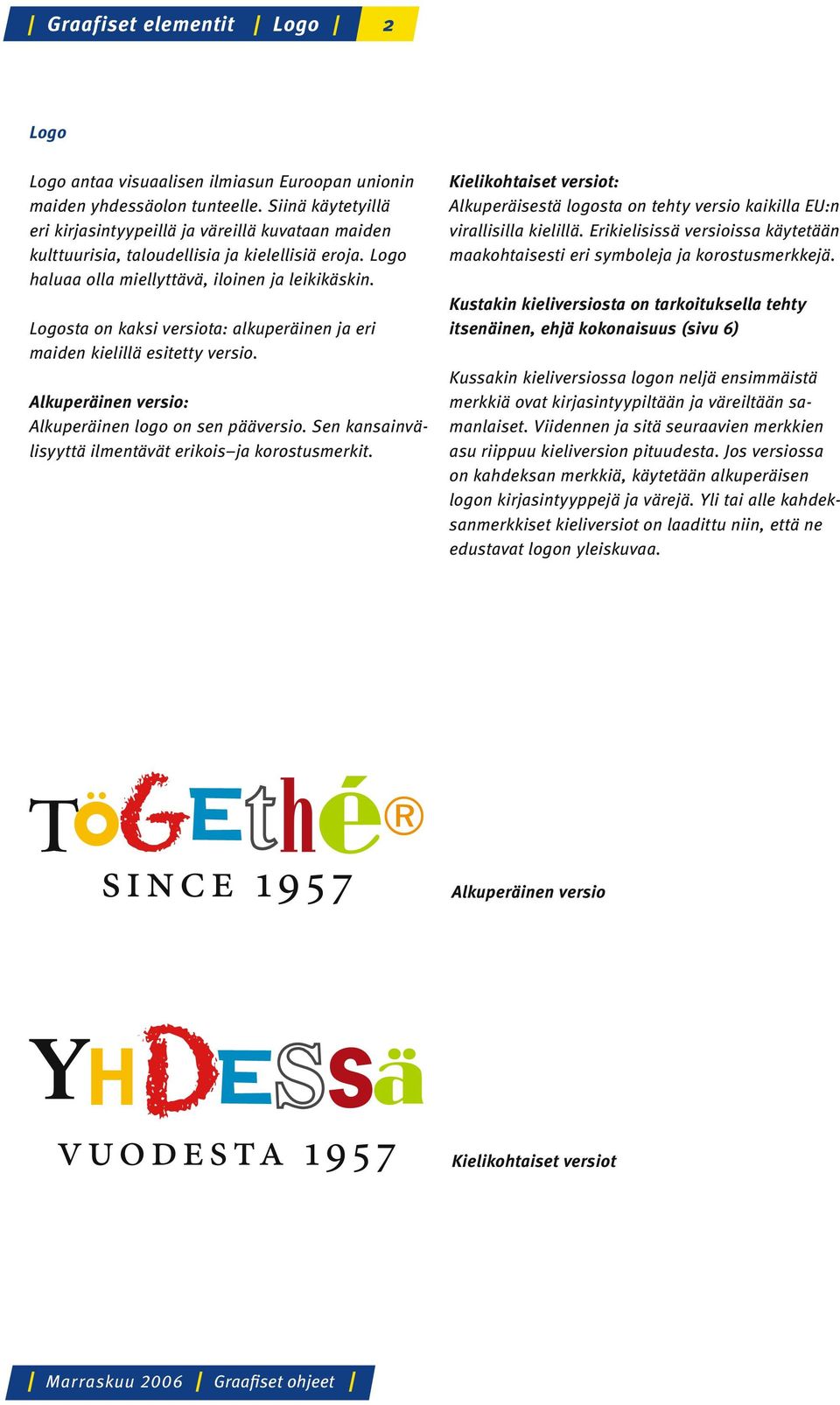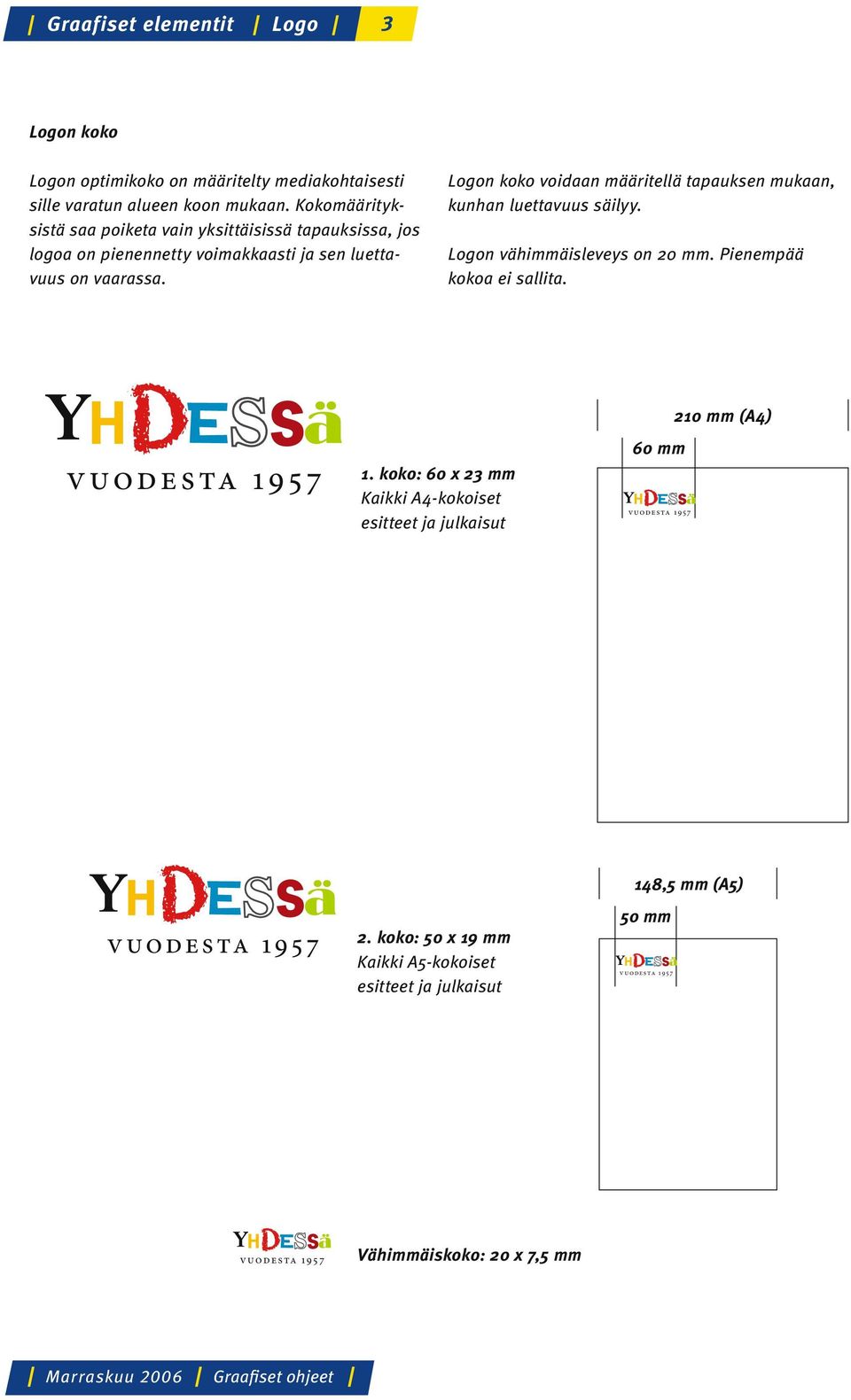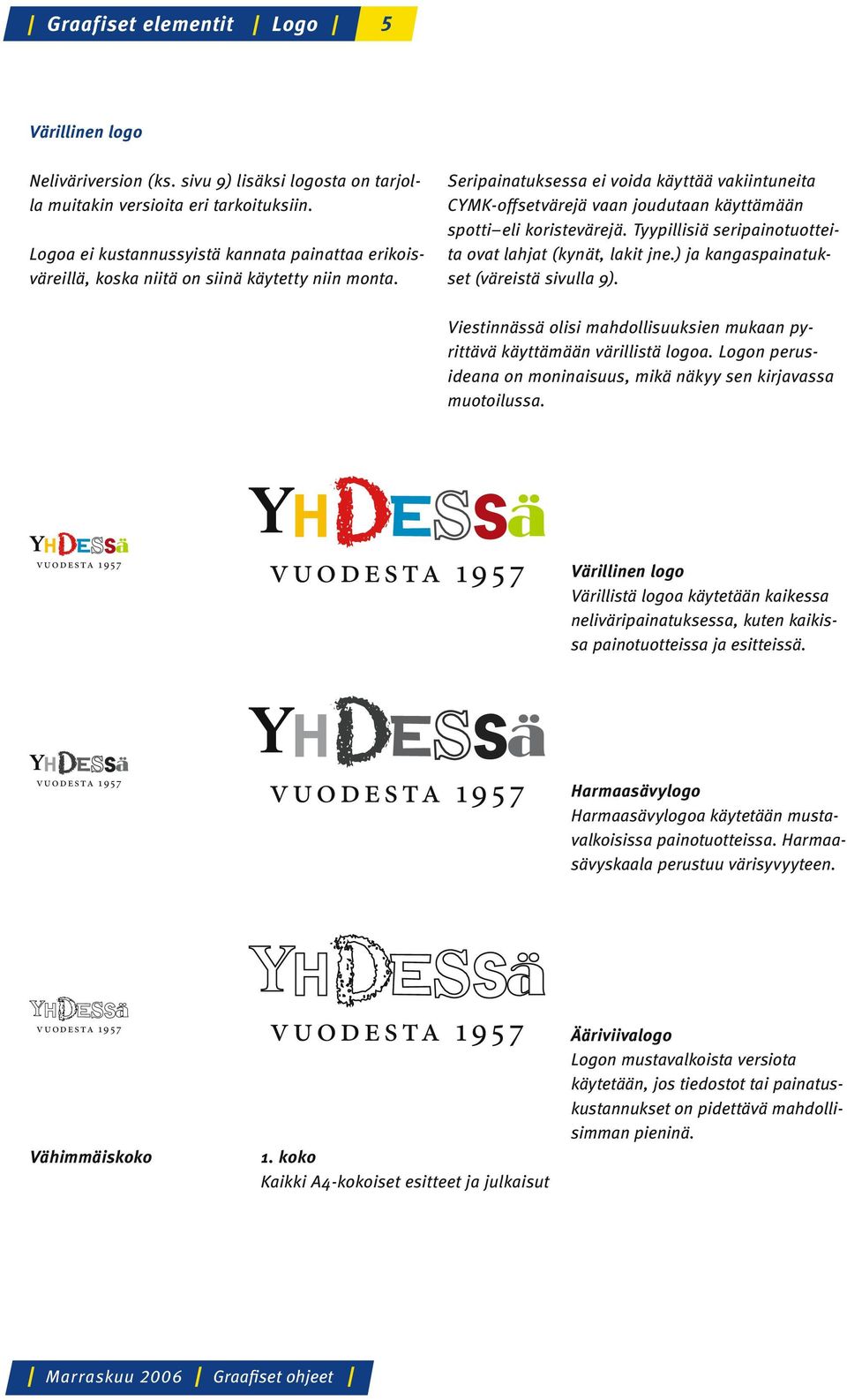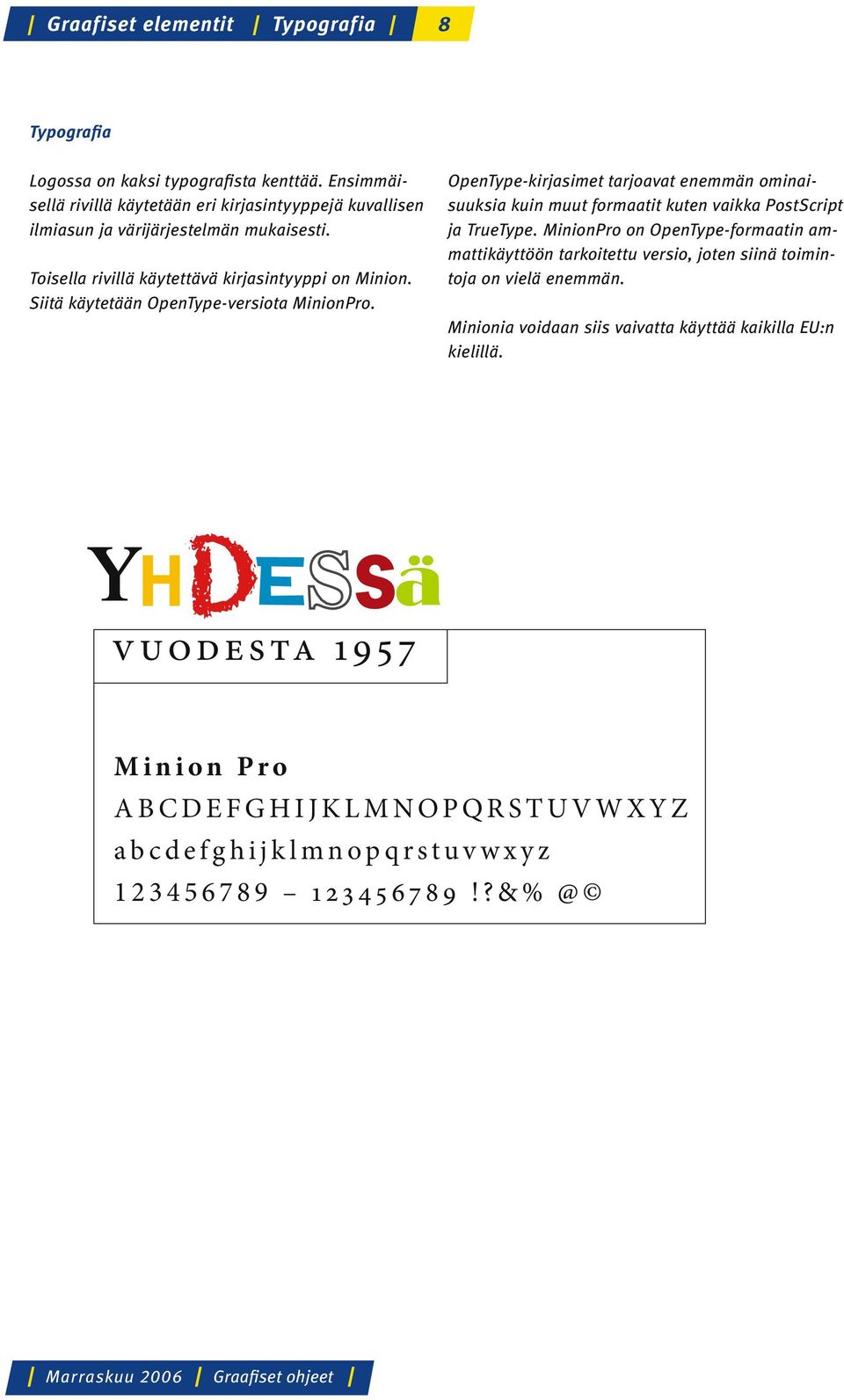
2 Graafiset elementit Logo 2 Logo Logo antaa visuaalisen ilmiasun Euroopan unionin maiden yhdessäolon tunteelle. Siinä käytetyillä eri kirjasintyypeillä ja väreillä kuvataan maiden kulttuurisia, taloudellisia ja kielellisiä eroja. Logo haluaa olla miellyttävä, iloinen ja leikikäskin. Logosta on kaksi versiota: alkuperäinen ja eri maiden kielillä esitetty versio. Alkuperäinen versio: Alkuperäinen logo on sen pääversio. Sen kansainvälisyyttä ilmentävät erikois ja korostusmerkit. Kielikohtaiset versiot: Alkuperäisestä logosta on tehty versio kaikilla EU:n virallisilla kielillä. Erikielisissä versioissa käytetään maakohtaisesti eri symboleja ja korostusmerkkejä. Kustakin kieliversiosta on tarkoituksella tehty itsenäinen, ehjä kokonaisuus (sivu 6) Kussakin kieliversiossa logon neljä ensimmäistä merkkiä ovat kirjasintyypiltään ja väreiltään samanlaiset. Viidennen ja sitä seuraavien merkkien asu riippuu kieliversion pituudesta. Jos versiossa on kahdeksan merkkiä, käytetään alkuperäisen logon kirjasintyyppejä ja värejä. Yli tai alle kahdeksanmerkkiset kieliversiot on laadittu niin, että ne edustavat logon yleiskuvaa. since 1957 Alkuperäinen versio Kielikohtaiset versiot
3 Graafiset elementit Logo 3 Logon koko Logon optimikoko on määritelty mediakohtaisesti sille varatun alueen koon mukaan. Kokomäärityksistä saa poiketa vain yksittäisissä tapauksissa, jos logoa on pienennetty voimakkaasti ja sen luettavuus on vaarassa. Logon koko voidaan määritellä tapauksen mukaan, kunhan luettavuus säilyy. Logon vähimmäisleveys on 20 mm. Pienempää kokoa ei sallita. 1. koko: 60 x 23 mm Kaikki A4-kokoiset esitteet ja julkaisut 60 mm 210 mm (A4) 2. koko: 50 x 19 mm Kaikki A5-kokoiset esitteet ja julkaisut 148,5 mm (A5) 50 mm Vähimmäiskoko: 20 x 7,5 mm
4 Graafiset elementit Logo 4 Suoja-alue on logon ympärillä oleva tila, jonka ansiosta logo erottuu läheisyydessä olevista graafisista elementeistä. Suoja-alueen koon perustana oleva yksikkö saadaan ensimmäisestä kirjaimesta, ja sen mittasuhteet määritellään suhteessa ensimmäisen kirjaimen kokoon. Suoja-aluetta on pidettävä vähimmäisvaatimuksena. Logon tausta voi olla yksivärinen joko valkoinen tai jokin vaalea väri. Logon ja EU:n lipun asemointi Jotta logon ja Euroopan unionin välille muodostuisi suora yhteys, logoa olisi käytettävä yhdessä EU:n lipun kanssa. Logon ja EU:n lipun väliin jätetään suoja-alue (optimi ja minimietäisyys), kuten alla havainnollistetaan. Logo on asetettava valkoiselle taustalle, jotta se on varmasti luettava. Siksi sekä logo että EU:n lippu olisi painotuotteissa hyvä sijoittaa valkoiselle palkille. Näin brändi olisi helposti tunnistettavissa. < = optimum distance between two logo 210 mm (A4) 60 mm < < < minimum distance between two logo
5 Graafiset elementit Logo 5 Värillinen logo Neliväriversion (ks. sivu 9) lisäksi logosta on tarjolla muitakin versioita eri tarkoituksiin. Logoa ei kustannussyistä kannata painattaa erikoisväreillä, koska niitä on siinä käytetty niin monta. Seripainatuksessa ei voida käyttää vakiintuneita CYMK-offsetvärejä vaan joudutaan käyttämään spotti eli koristevärejä. Tyypillisiä seripainotuotteita ovat lahjat (kynät, lakit jne.) ja kangaspainatukset (väreistä sivulla 9). Viestinnässä olisi mahdollisuuksien mukaan pyrittävä käyttämään värillistä logoa. Logon perusideana on moninaisuus, mikä näkyy sen kirjavassa muotoilussa. Värillinen logo Värillistä logoa käytetään kaikessa neliväripainatuksessa, kuten kaikissa painotuotteissa ja esitteissä. Harmaasävylogo Harmaasävylogoa käytetään mustavalkoisissa painotuotteissa. Harmaasävyskaala perustuu värisyvyyteen. Vähimmäiskoko 1. koko Kaikki A4-kokoiset esitteet ja julkaisut Ääriviivalogo Logon mustavalkoista versiota käytetään, jos tiedostot tai painatuskustannukset on pidettävä mahdollisimman pieninä.
6 Graafiset elementit Logo 6 Logon kielikohtaiset versiot Alkuperäisestä logosta on tehty versio EU:n kaikilla virallisilla kielillä. Kaikkiin määriteltyihin versioihin (väri-, harmaasävy ja ääriviivaversio) on tehty kielikohtaisia mukautuksia. Järjestely on kuvattu sivulla 2. Alkuperäinen versio BG bulgaria CS tšekki since 1957 ot 1957 od 1957 DA tanska DE saksa EL kreikka siden 1957 EN englanti seit 1957 ES espanja ΑΠO TO 1957 ET viro since 1957 aastast 1957 desde 1957 FI suomi FR ranska GA iiri depuis 1957 ó 1957 HU unkari IT italia LT liettua dal óta nuo 1957-ųjų LV latvia MT malta NL hollanti mill-1957 kopš gada sinds 1957 PL puola PT portugali RO romania od 1957 din 1957 desde 1957 SK slovakki SL sloveeni SV ruotsi od 1957 sedan 1957
7 Graafiset elementit Logo 7 Mitä ei saa tehdä Periaatteena on, ettei logoa muuteta. Sitä ei saa muokata millään tavoin. Logoa ei saa skaalata eikä vääristää. Muita kirjasinleikkauksia ei saa käyttää. Ainoastaan tässä määritellyt väriversiot ovat sallittuja. Logon elementtien sijoittelua ei saa muuttaa. S I N C E
8 Graafiset elementit Typografia 8 Typografia Logossa on kaksi typografista kenttää. Ensimmäisellä rivillä käytetään eri kirjasintyyppejä kuvallisen ilmiasun ja värijärjestelmän mukaisesti. Toisella rivillä käytettävä kirjasintyyppi on Minion. Siitä käytetään OpenType-versiota MinionPro. OpenType-kirjasimet tarjoavat enemmän ominaisuuksia kuin muut formaatit kuten vaikka PostScript ja TrueType. MinionPro on OpenType-formaatin ammattikäyttöön tarkoitettu versio, joten siinä toimintoja on vielä enemmän. Minionia voidaan siis vaivatta käyttää kaikilla EU:n kielillä. Minion Pro ABCDEFGHIJKLMNOPQRSTUVWXYZ abcdefghijklmnopqrstuvwxyz
9 Graafiset elementit Värit 9 Värit Logossa on käytetty kuutta väriä sekä mustaa ja harmaata. CMYK-värimallin värit syaani, magenta, keltainen ja musta ovat modernin neliväripainannan tekninen perusta. Digitaaliseen käyttöön soveltuu taas RGB-värimalli. Mallin perustana ovat päävärit punainen, vihreä ja sininen, ja se täyttää sähköisten näyttölaitteiden asettamat vaatimukset. CMYK * (4c, euroskaala) ja erikoisvärit Tiivistelmä painannassa ja sähköisissä medioissa käytettävistä väreistä: Painotalossa painatettu tiedotus ja viestintämateriaali: CMYK (euroskaala) Digitaalinen ja itse painettu tiedotus ja viestintämateriaali: RGB Erikoisvärejä (Pantone) käytetään vain seripainatuksessa. Kohteita ovat erityisesti lahjat ja kangaspainatukset (sivu 5). RGB (punainen vihreä sininen) Musta (Pantone Process Black) Musta Keltainen (Pantone 123) Keltainen Punainen (Pantone 485) Punainen Sininen (Pantone Process Cyan) Sininen Harmaa (Pantone 425) Harmaa Rubiinpunane (Pantone 1805) Rubiinpunane Vihreä (Pantone 390) Vihreä Oranssi (Pantone 152) Oranssi * C=syaani M=magenta Y=keltainen K=musta